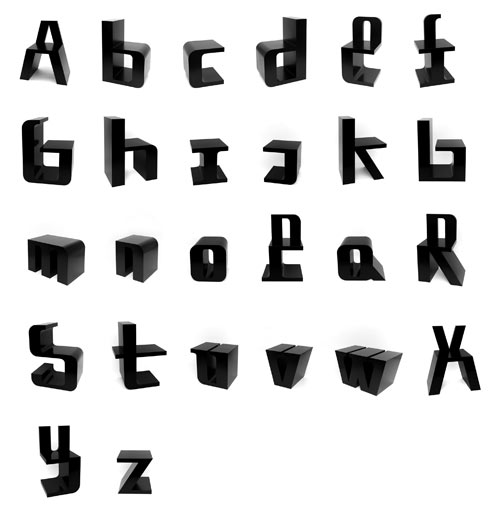
diese Stühle hab ich grad im designer daily
entdeckt:
Cool schon. Bleibt nur die Frage welcher davon am bequemsten ist. Ich tendiere ja zu b oder d. Bei g und s hat man dauernd was im Rücken …
Cool schon. Bleibt nur die Frage welcher davon am bequemsten ist.
Das ist Kunst. Die muß per definitionem unbequem sein.
Ich tendiere ja zu b oder d.
Man muß schon das ganze Alphabet dastehen haben, einige Buchstaben am besten mehrfach. Dann kann man auch mit der Sitzordnung subtile Botschaften ausdrücken.
Bei g und s hat man dauernd was im Rücken …
Das ist die Halswirbelstütze. :!:
… Dann kann man auch mit der Sitzordnung subtile Botschaften ausdrücken.
Oh super, das eröffnet ganz neue Möglichkeiten!
Unerwünschter Besuch bekommt ein »i« … :wink:
Aber von diesen Stühlen will man doch mehr haben, nicht weniger … :wink:
Meh ... Ich hab da Schwierigkeiten Buchstaben zu erkennen, geschweige denn Stühle ... nudgenudge.gif
Wenns schon Novelty sein muss, dann lieber einen von den beiden:
Der Minimalist*
Wenn ich sitze, will ich nicht
sitzen, wie mein Sitz-Fleisch möchte,
sondern wie mein Sitz-Geist sich,
säße er, den Stuhl sich flöchte.
Der jedoch bedarf nicht viel,
schätzt am Stuhl allein den Stil,
überläßt den Zweck des Möbels
ohne Grimm der Gier des Pöbels.